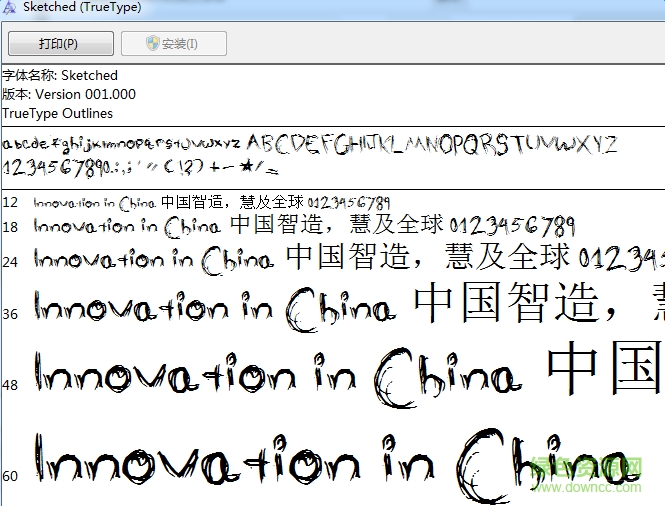
Sketched字體是一款極具個(gè)性的英文字體,文字排版、海報(bào)廣告設(shè)計(jì)、藝術(shù)設(shè)計(jì)等方面都可以使用,小編為大家?guī)砻赓M(fèi)下載地址,大家快來綠色資源網(wǎng)踴躍下載哦!
Sketched字體,一款非常好看的個(gè)性英文字體,字形飄逸秀氣,書寫流暢,可用于排版方面。喜歡的朋友就趕快來綠色資源網(wǎng)下載使用吧!